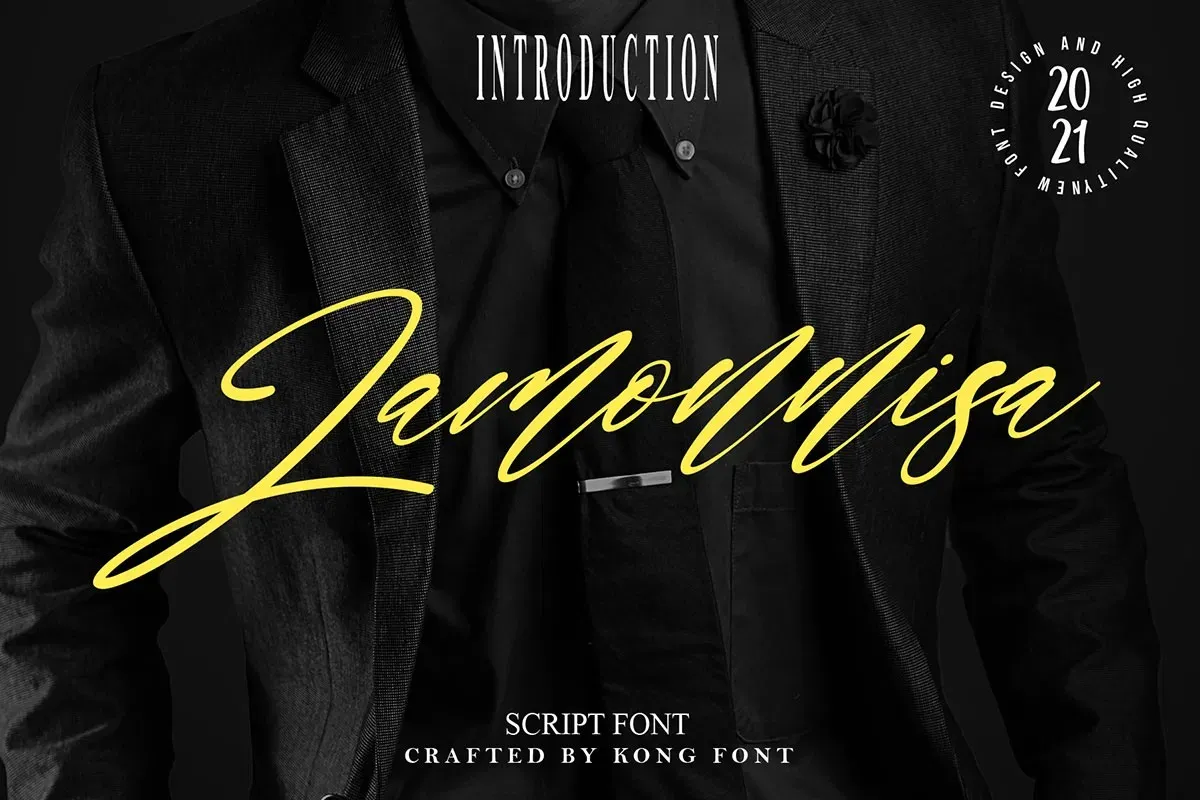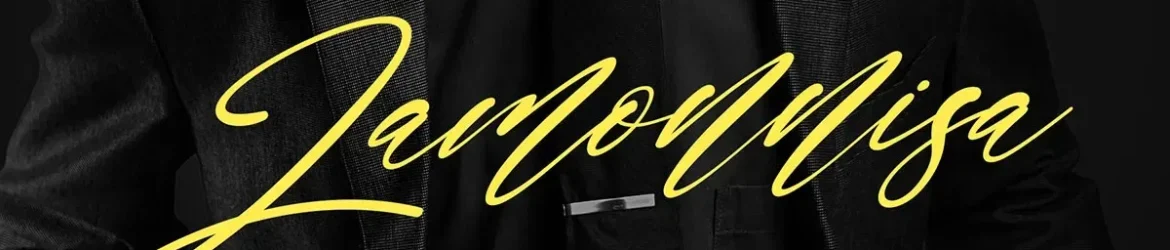
Lamonnisa Font – Download Grátis
A Lamonnisa Font é uma elegante escolha para designers que valorizam um estilo natural e autêntico em seus projetos digitais. Com seu carácter feito à mão, a Lamonnisa oferece uma sensação de frescor e naturalidade, ideal para aplicativos como banners, flyers ou materiais gráficos digitais. Este script font é perfeito para incorporar um toque único ao seu design, proporcionando um resultado que se destaca no meio da sua paleta visual. A Lamonnisa é uma excelente opção para quem procura uma fonte de escrita natural e autêntica, capaz de transmitir emoções e criar uma conexão direta com o público alvo sem ser vulgar ou exagerado. Escolha a Lamonnisa Font da 99designs para enriquecer seu design digital.